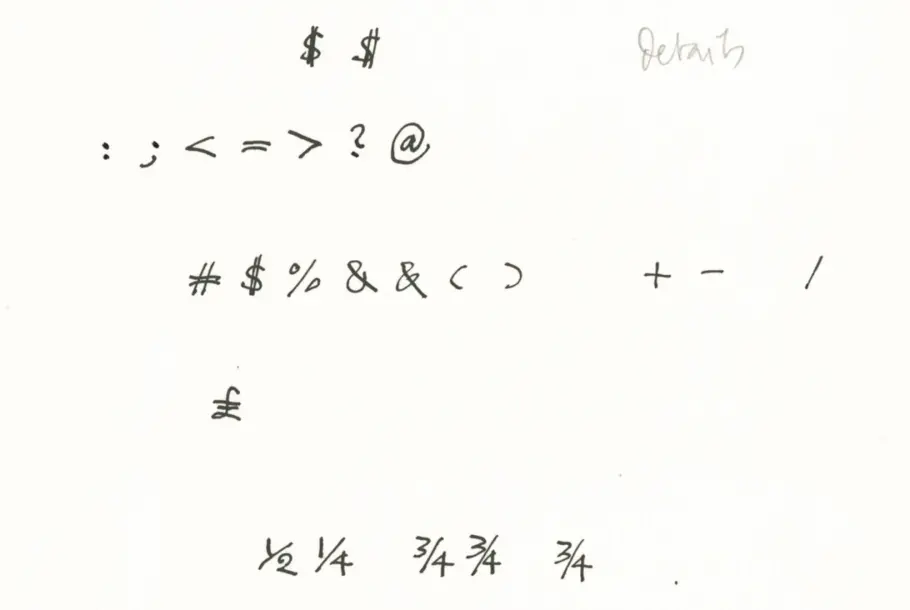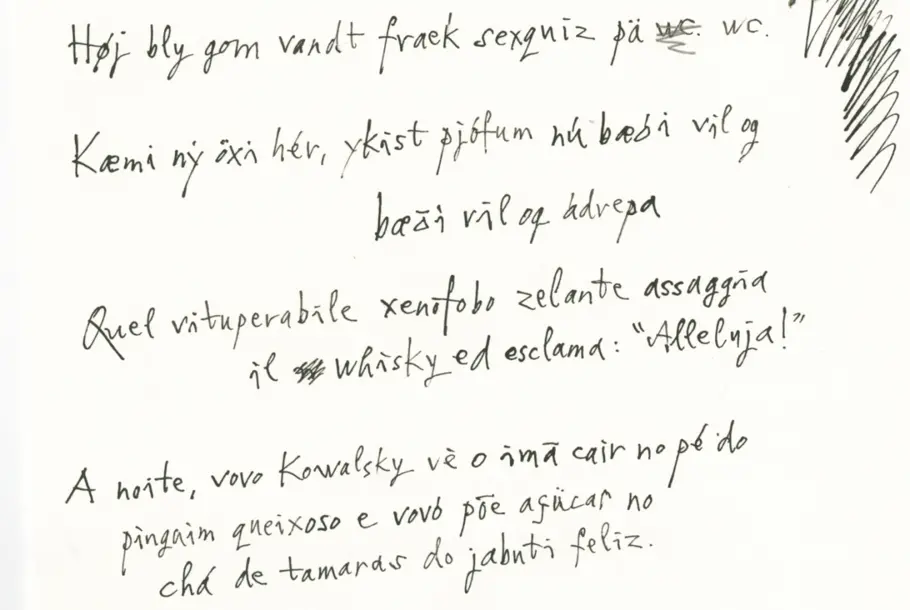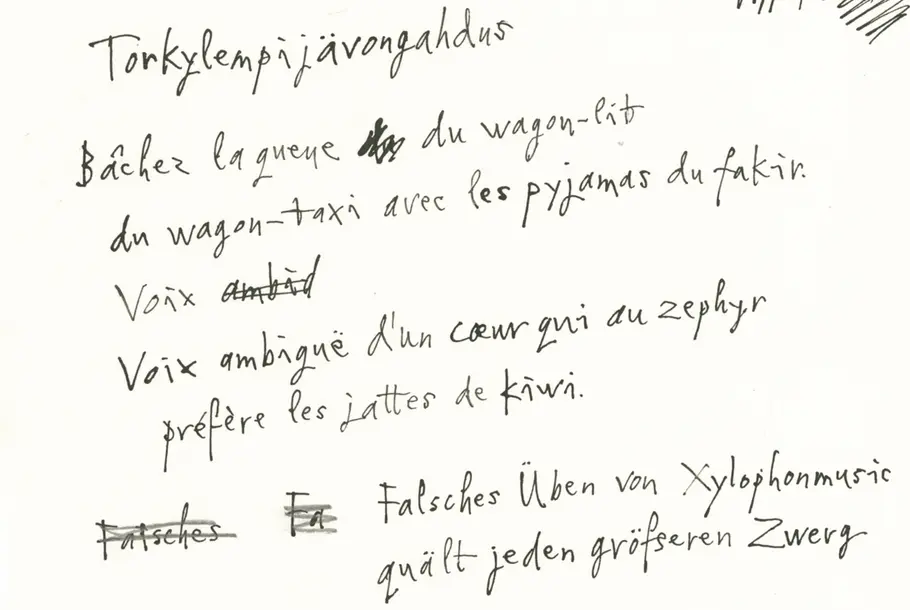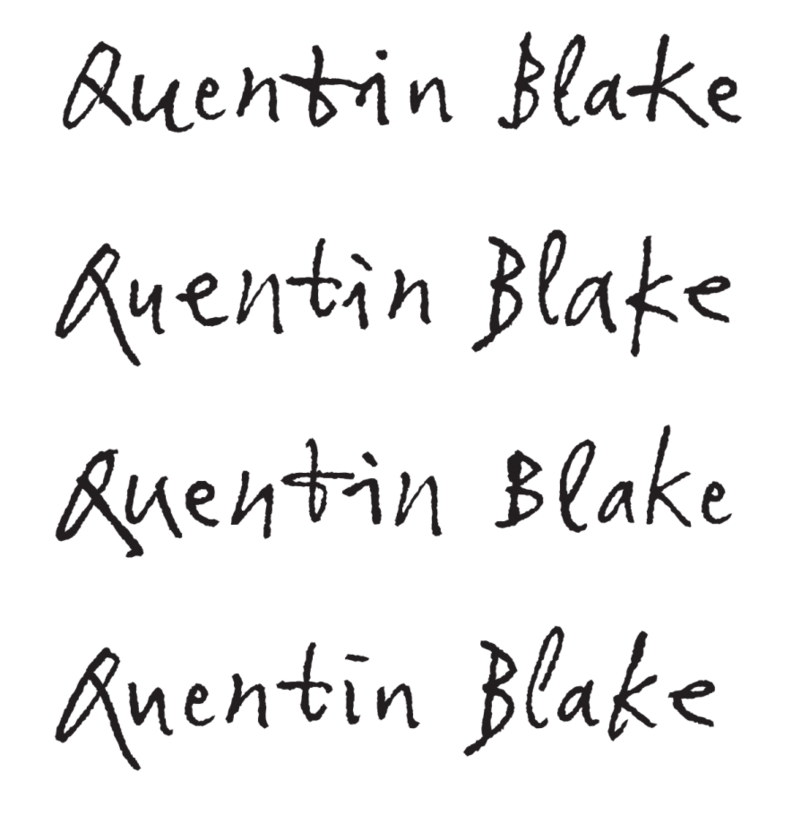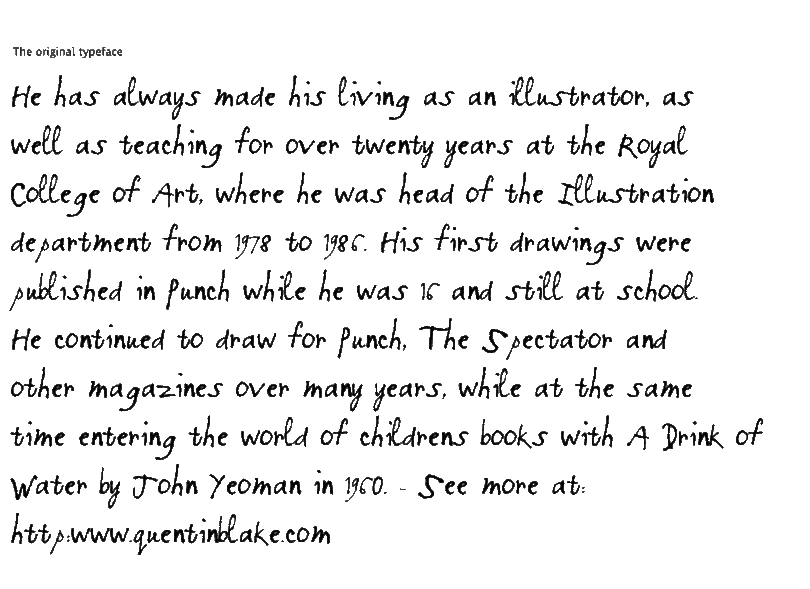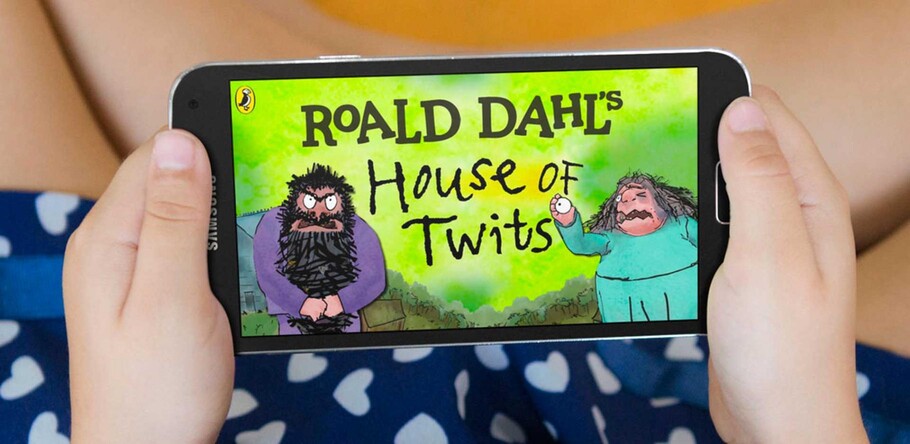
Une police d’écriture sur mesure pour Sir Quentin Blake.
“ La police finale ne se contente pas de ressembler à l’écriture de Sir Quentin Blake, elle agit comme telle.
Monotype a travaillé avec le célèbre illustrateur Sir Quentin Blake et son équipe pour recréer son écriture sous la forme d’une police de caractères sur mesure.
Le contexte
S’il y a un mot qui vient à l’esprit quand on pense à l’œuvre de Sir Quentin Blake, c’est la joie. Étant l’un des illustrateurs les plus éminents et les plus appréciés au monde, son art – qu’il se retrouve dans ses célèbres collaborations avec Roald Dahl, dans sa propre collections de livres primés ou dans des salles d’exposition – a permis à des centaines de personnages de bondir depuis la page jusqu’au cœur des enfants (et des grands enfants) du monde entier.
Son style ludique est particulièrement évident dans son écriture. Avec ses formes distinctives et son placement irrégulier, elle est indéniablement sienne et est souvent tout aussi demandée que ses illustrations, que ce soit pour la couverture d’un livre, d’une publication ou d’un autre support commercial. En outre, il soutient depuis longtemps de nombreuses organisations et projets caritatifs, et on lui demande régulièrement d’écrire des noms ou des phrases à afficher en signe de son soutien. Sans surprise, c’est un homme très occupé.
“ L’écriture de Quentin est tout sauf régulière, mais elle n’est pas totalement aléatoire non plus. Il y a quelque chose qui nous permet de dire que c’est la sienne – tout comme aucun nuage n’est identique à un autre et n’a de forme définie, mais quand vous en voyez un dans le ciel, vous pouvez toujours dire que c’est un nuage.
Une police de caractère dans le style de son écriture avait été créée pour être utilisée dans l’édition il y a quelques années, mais, au fil du temps, ses limites étaient devenues plus visibles. Blake et son équipe se sont tournés vers Monotype pour créer une nouvelle police de caractères qui pourrait contribuer à alléger le poids de la demande sur son temps et répondre à une plus grande variété de besoins.
Le défi
Jetez un œil à votre écriture et vous serez en mesure de repérer les détails qui la rendent unique, que ce soit l’arc d’un neuf, une barre sur un t ou une boucle sur un g. Pour que cette nouvelle police soit un succès, elle devait imiter les propres idiosyncrasies de Blake : la hauteur réduite et variable des minuscules, l’épaisseur imprévisible des traits, les traverses et les queues exagérées. Elle devait également être flexible, reprendre le même rythme et l’espacement utilisé lors de la création d’une lettre à la main. Enfin, elle devait répondre à une demande de langues internationales pour aider à relever les défis les plus chronophages : « Les demandes de langues différentes peuvent être assez difficiles s’il ne les connaît pas », explique Liz Williams, l’archiviste de Blake. « Il doit examiner attentivement chaque lettre pour s’assurer qu’elle est correcte et cela peut nuire au flux naturel. »
Le brief était simple, bien que difficile : créer une police qui reflète la forme unique de l’écriture de Blake d’une manière authentique et naturelle. Pas seulement la forme des lettres, mais la façon dont il choisit de les placer.
La police d’écriture originale de Quentin et la nouvelle version de Monotype.
La solution
À partir d’écritures originales à l’encre de Blake, Toshi Omagari, designer typographique chez Monotype, a commencé à sélectionner et à redessiner des lettres, des chiffres et des symboles individuels, mais il est vite apparu que cette technique faisait perdre une partie du flux de l’écriture originale. Toshi est retourné voir Blake pour obtenir d’autres échantillons, cette fois écrits en phrases et en pangrammes.
Il a ensuite sélectionné pour chaque caractère quatre alternatives subtilement différentes qui, combinées, donnent au texte un rendu suffisamment aléatoire pour paraître authentique, tout en gardant un jeu de glyphes facile à gérer. L’important était de trouver l’équilibre entre variété et régularité : «Sans variantes, les polices manuscrites courent le risque de paraître peu naturelles, alors qu’avec trop de variantes, elles peuvent devenir ingérables, explique Toshi. L’écriture de Quentin est tout sauf régulière, mais elle n’est pas totalement aléatoire non plus. Il y a quelque chose qui nous permet de dire que c’est la sienne – tout comme aucun nuage n’est identique à un autre et n’a de forme définie, mais quand vous en voyez un dans le ciel, vous pouvez toujours dire que c’est un nuage.”
Des exemples d’écriture du nom de Quentin Blake ont été générés de diverses manières, en utilisant des alternatives subtilement différentes.
Chacun des caractères alternatifs a été choisi sur la base de sa taille, de sa ressemblance et de sa clarté : ni trop grand ni trop petit, ni trop similaire, l’encre pas trop maculée. Au besoin, des glyphes supplémentaires pour les caractères qui ne pouvaient pas être capturés de manière cohérente, principalement des lettres non anglaises et des symboles peu courants, ont été dessinés dans le style de Blake. L’apparence générale devait être naturelle : « Je ne voulais pas que quelque chose ait l’air trop unique, surtout pour les voyelles qui apparaissent plus fréquemment, parce que les gens remarqueraient celles qui ressortent, sont répétées, et se rendraient compte qu’il s’agit d’une police, ajoute Toshi. Il fallait une apparence aléatoire et qui cache le fait que ce n’est pas son écriture réelle. »
Ce même principe s’applique pour le crénage, Toshi prenant soin de ne pas trop régulariser l’espacement afin de conserver les irrégularités caractéristiques de l’écriture. Ce n’était pas une mince affaire : avec quatre séries de variantes, cela signifiait que chaque glyphe était d’abord crénelé par rapport aux autres dans sa propre série, puis par rapport aux glyphes des autres séries (au total, le crénage a été testé dans près de 25 permutations). Toutes les ligatures qui figuraient dans l’écriture de Blake ont également été soigneusement équilibrées. Les lettres comme le t, aux traverses traînantes et allongées, étaient plus difficiles à placer. Elles ont donc été un peu plus ajustées pour s’assurer qu’elles touchaient bien les caractères voisins.